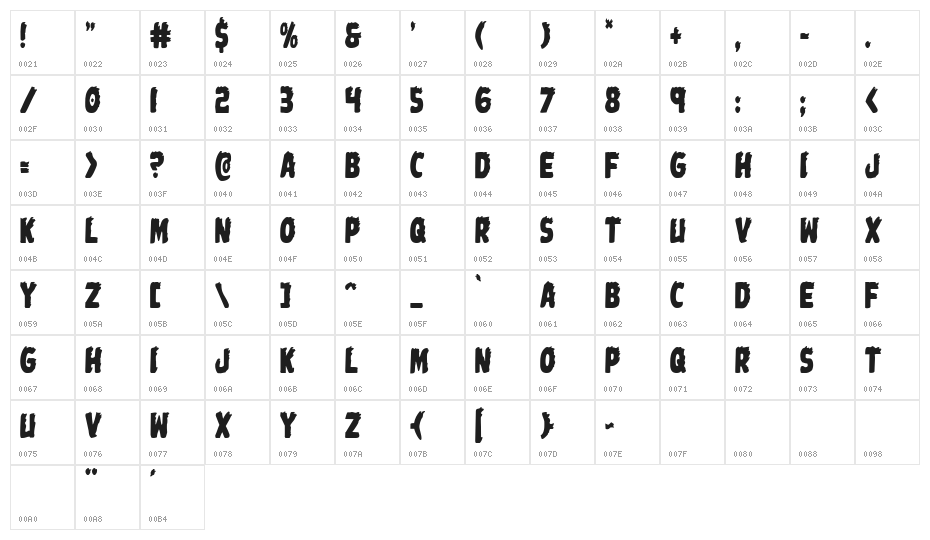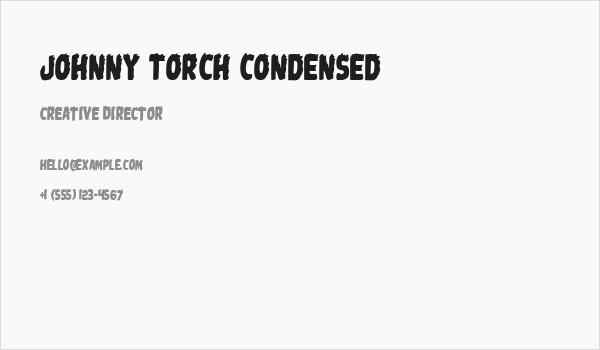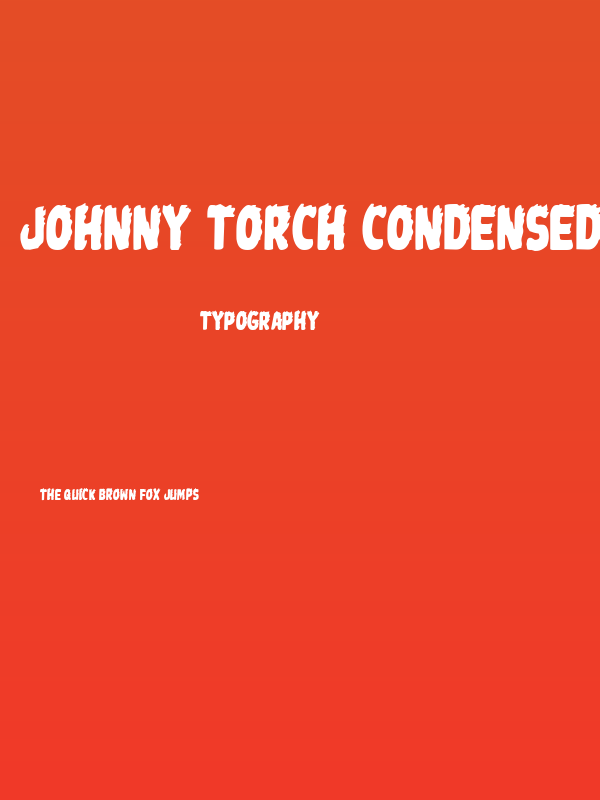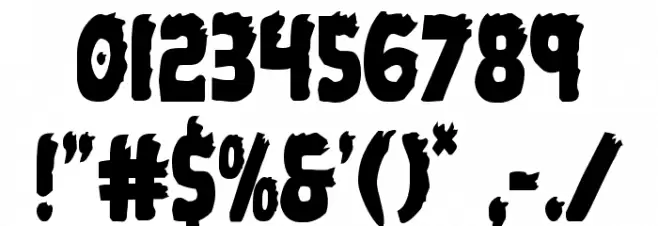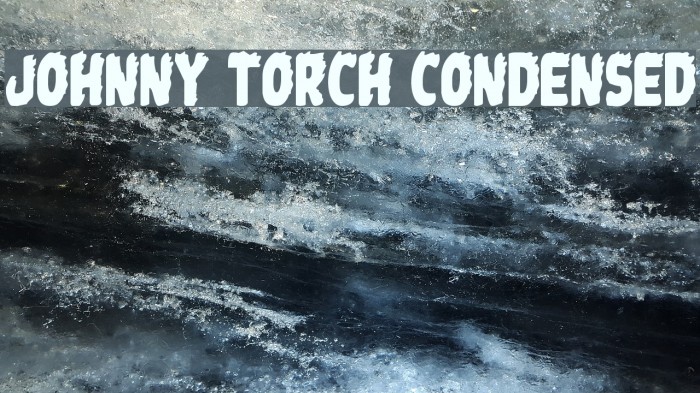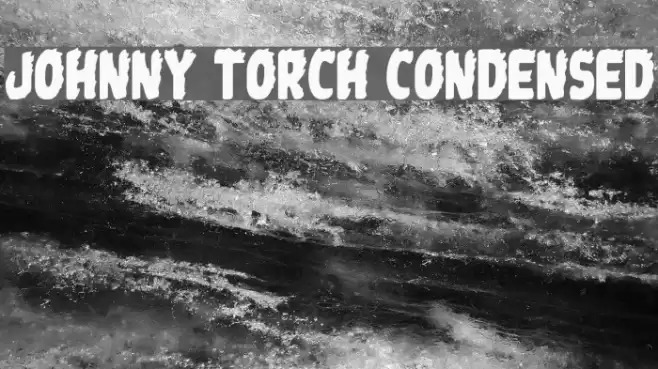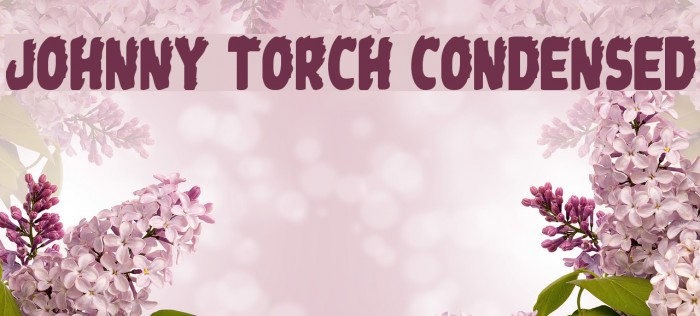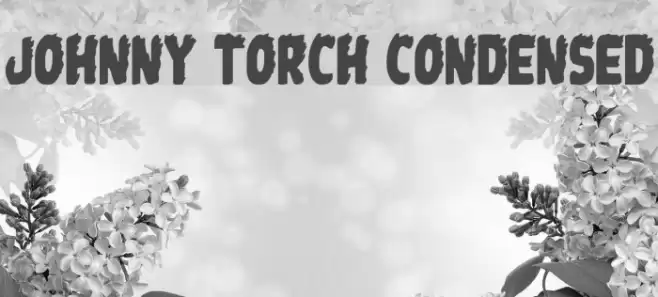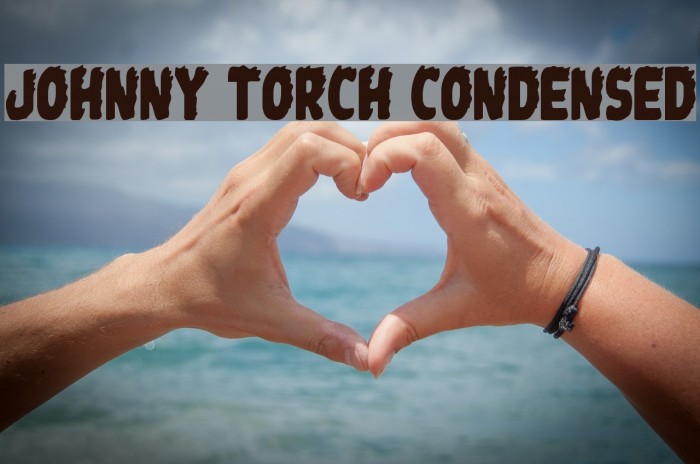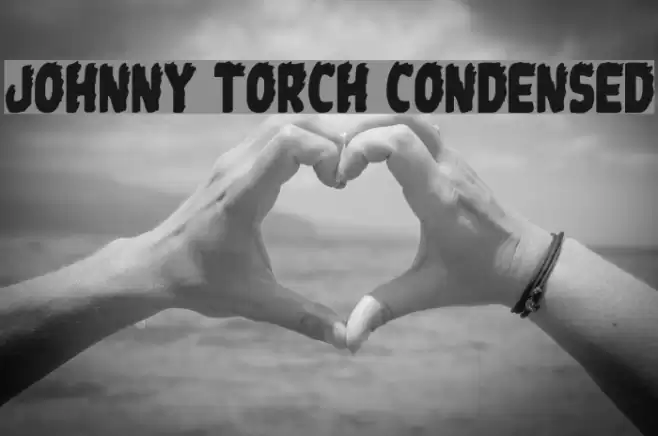
Johnny Torch Condensed Font
| Projetos propostos | Ideal for poster designs, branding projects, album covers, and any creative work that requires a bold, eye-catching typeface. |